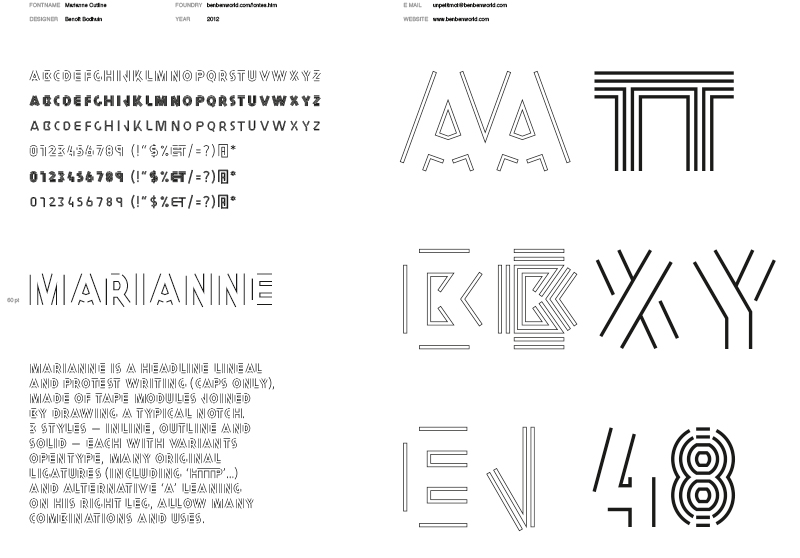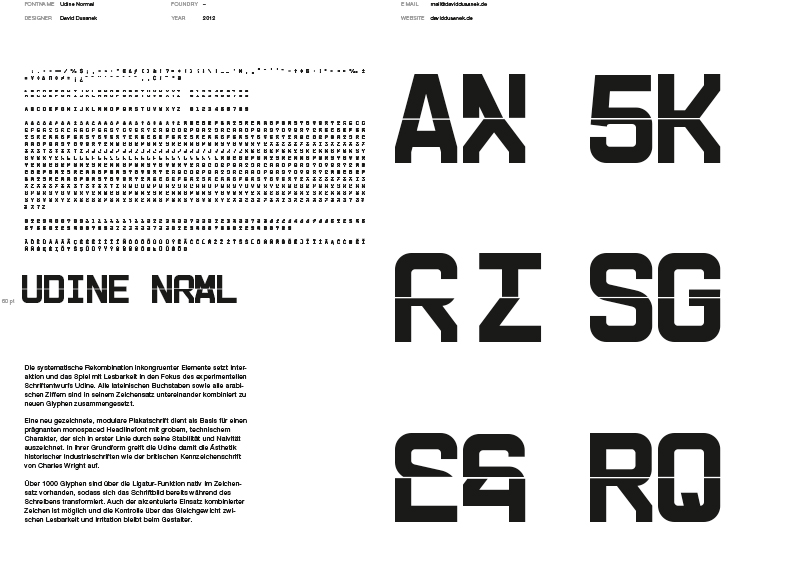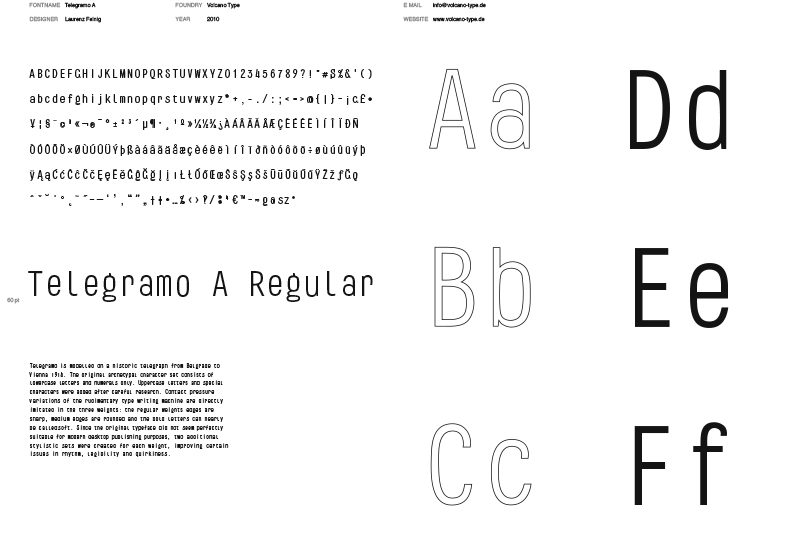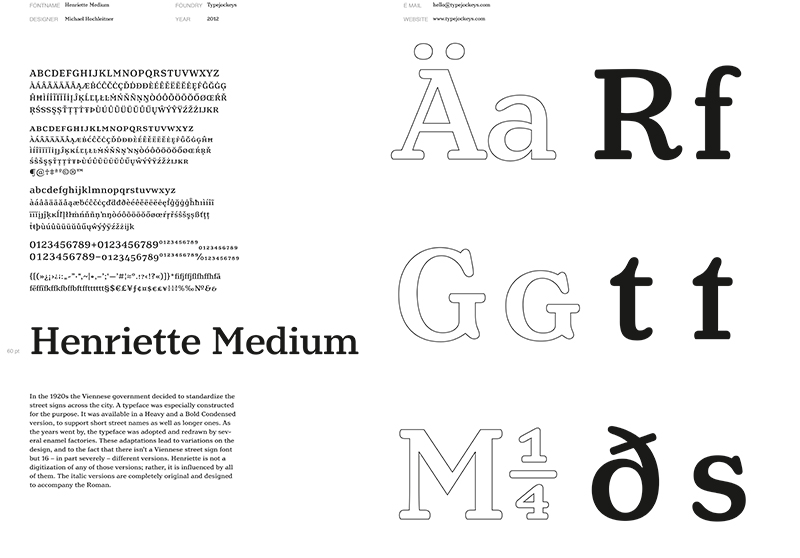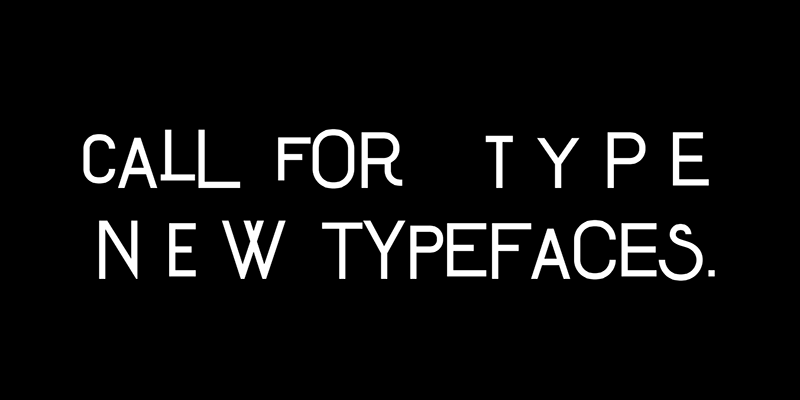
Auf große internationale Resonanz stieß der Wettbewerb »Open Call for Type«, der vom Mainzer Gutenberg-Museum und dem Institut Designlabor Gutenberg / FH Mainz ausgelobt wurde: 290 Schriftentwürfe aus mehr als 17 Ländern, von »A« wie Argentinien bis »U« wie USA, verdeutlichen auf eindrucksvolle Weise den Stand des aktuellen Type-Designs. Ausgewählt wurden 50 Schriftentwürfe für die Ausstellung »Call for Type«, die ab dem 6. Juni im Mainzer Gutenberg-Museum gezeigt wird.
In der Tat repräsentieren die eingereichten Schriften den aktuellen Stand des jungen Type-Designs: Das Spektrum reicht von studentischen Entwürfen bis hin zu großen Type-Foundries. Begeistert vom der Internationalität und der großen Bandbreite der Entwürfe zeigte sich Dr. Annette Ludwig, Direktorin des Gutenberg-Museums und Jury-Mitglied. Dies sei auch ein Hinweis dafür, dass der seit 2010 in der Zusammenarbeit zwischen Museum und FH etablierte Schwerpunkt Typografie von den verschiedensten Zielgruppen wahrgenommen wird. Der international renommierte Type Designer Akira Kobayashi, Type Director bei Monotype und Jury-Mitglied, äußerte sich erstaunt über das hohe Niveau und die Qualität der eingereichten Entwürfe. Dass das Niveau höher ausgefallen sei als erwartet, bestätigte auch Lars Harmsen, Professor an der FH Dortmund, der diese positive Entwicklung auch auf die verstärkte Konzentration auf Typografie in der Ausbildung von Designern in den letzten Jahren zurück führt. Er warnt dennoch davor, Schrift und Schriftentwurf über zu bewerten. Schließlich sei Schrift »nur« ein Werkzeug; erst der gestalterische Umgang mit ihr könne eine qualitätvolle Gestaltung erzeugen. Es gehe, so Harmsen, schließlich um das Abarbeiten am strengen Spiel der Regelhaftigkeit.
So ist nach den gestalterischen Experimenten und Formexzessen der letzten Jahre im Font-Design heute eine deutliche Abklärung zu verzeichnen – Schriftgestaltung wird sehr ernst genommen: Es geht wieder um Lesbarkeit und funktionale Aspekte, gepaart mit einer Liebe zum gestalterischen, durchaus auch ungewöhnlichen Detail, die letztlich die Professionalität und Qualität der jungen Fonts auszeichnet. Deutlich wurde aber auch, dass Schriften heute sehr umfangreich ausgebaut werden: Eingereicht wurden nicht nur zahlreiche Schnitte, sondern auch Glyphen und Ornamente sowie kyrillische und/oder arabische Fonts – ein deutlichen Zeichen dafür, dass junge Gestalterinnen und Gestalter selbstverständlich ganz unterschiedliche Kulturkreise im Blick haben. Dies sei, so Isabel Naegele, Jurymitglied, Professorin an der Mainzer FH und Mitorganisatorin, deutlich der Vernetzung junger Designerinnen und Designer über Ländergrenzen hinaus geschuldet. Zudem, so betonte Petra Eisele, ebenfalls Professorin an der FH Mainz, Jurymitglied und Mitorganisatorin, würden »klassische historische Vorbilder analysiert und neu interpretiert – nicht nur als Hommage an die großen Meister, sondern auch als Schulung des eigenen Qualitätsanspruches. Schließlich sei die »eigene« Schrift angesichts immer austauschbarer werdender globaler Gestaltungsmittel auch als bedeutendes Identifikationsmittel für junge Designerinnen und Designer zu begreifen.
Der Wettbewerb »Call for Type« wurde vom Mainzer Gutenberg-Museum und dem Designlabor Gutenberg / FH Mainz international ausgelobt. Eingereicht wurden 290 Schriftentwürfe aus mehr als 17 Ländern – von »A« wie Argentinien bis »U« wie USA«.
Jury:
Prof. Dr. Petra Eisele, Professorin für Designgeschichte und -theorie, Designlabor Gutenberg, FH Mainz
Prof. Lars Harmsen, Professor für Konzeption und Entwurf / Typografie und Layout, FH Dortmund
Bernhard Hofmacher, Specialist Designer Liaison, Monotype
Akira Kobayashi, Type Director, Monotype
Dr. Annette Ludwig, Direktorin Gutenberg-Museum Mainz
Prof. Dr. Isabel Naegele, Professorin für Gestaltungsgrundlagen und Typgrafie, Designlabor Gutenberg, FH Mainz
Robin Scholz, Studentischer Vertreter, Studiengang Kommunikationsdesign, FH Mainz
Die Sonderausstellung »Call for Type. New Typefaces / Neue Schriften«, bei der 20 ausgewählte Type-Designer sowie die 50 nun jurierten Fonts präsentiert werden, wird am 6. Juni im Mainzer Gutenberg-Museum eröffnet. Im Rahmenprogramm finden am 7. und 8. sowie am 19. Juni jeweils um 18.30 Uhr »Talks« über Schrift statt, bei denen international renommierte Gestalterinnen und Gestalter über ihre Schriftentwürfe berichten. Zudem wird mit der »Imprint Fair« am 8. Juni eine Messe für Schriftgestalter und Schriftverleger aus ganz Europa veranstaltet.
Call for Type. New Typefaces / Neue Schriften.
Sonderausstellung im Gutenberg-Museum Mainz
Zur Ausstellung erscheint der Katalog »Call for Type. New Typefaces / Neue Schriften.«